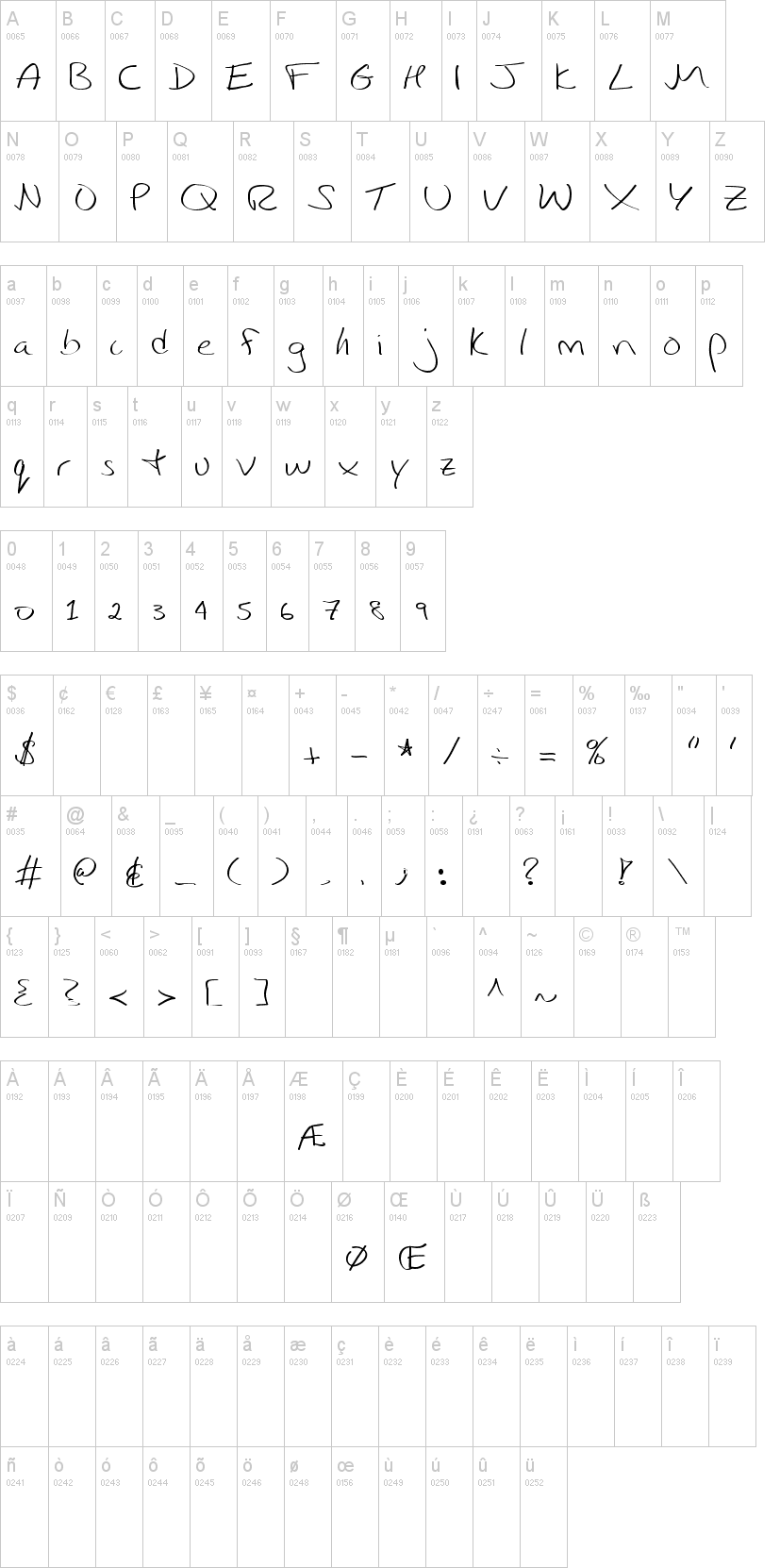
Ibarra 字体是一种现代、抽象的西班牙语字体,由著名的西班牙设计师Juanjo López Ibarra设计。Ibarra字体以简洁的线条和平衡的比例为特色,被认为是一种优雅而精致的字体。它有着清晰的字形,可以很好地表达文字的含义,使用起来非常方便。Ibarra字体适用于各种文字,特别适合用于宣传和标志,也可以用于网页设计、平面设计等多种应用场景。内容介绍
Ibarra是一款非常不错的手写艺术字体,具有很好的视觉感,适合于文化类的宣传设计、商业类品牌的广告和产品包装设计以及个性化文字排版等较多场景。